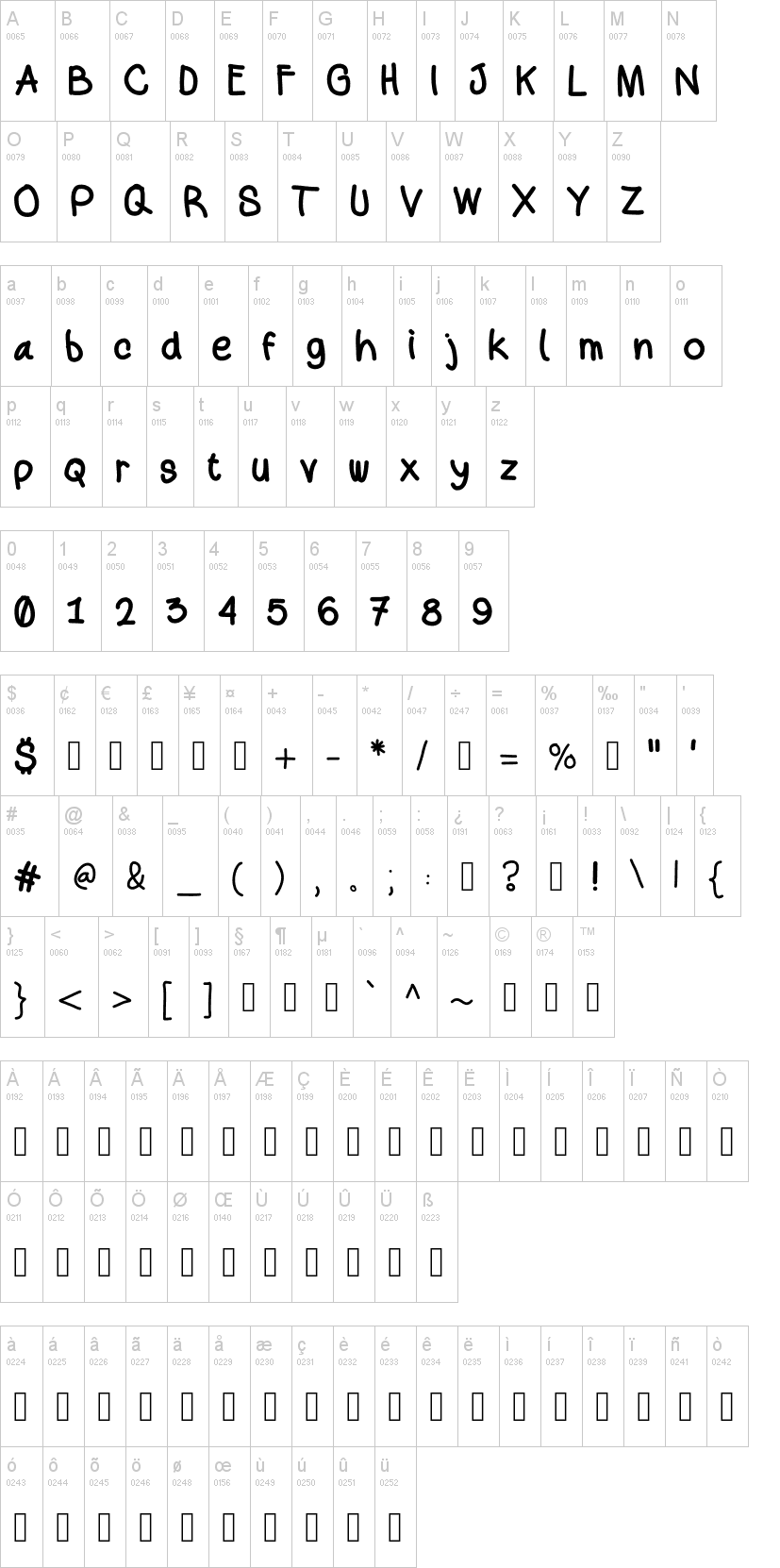
Abandonation是一种自由字体,由设计师Josip Kelava创作,它是一种简单而现代的字体,它的设计灵感来自文艺复兴时期的字体,但又具有现代感。Abandonation的字形极其简洁,只有一种字重,具有极佳的可读性和可用性,可以用于任何场景,包括标题、正文、标签等。Abandonation的字体也可以用于报纸、杂志、网页、平面设计等多种应用场景,它拥有极佳的可读性和可用性,可以帮助您在设计中轻松实现统一的视觉效果。内容介绍
Abandonation是一款非常不错的手写艺术字体,具有很好的视觉感,适合于文化类的宣传设计、商业类品牌的广告和产品包装设计以及个性化文字排版等较多场景。